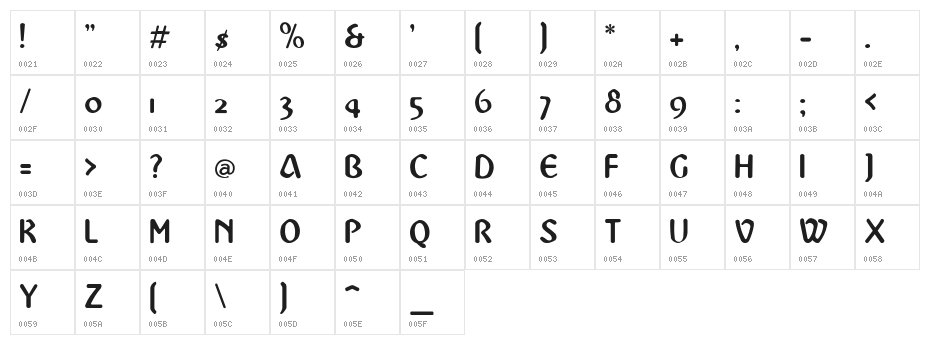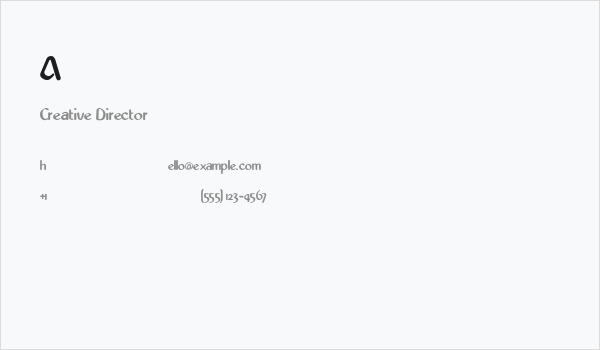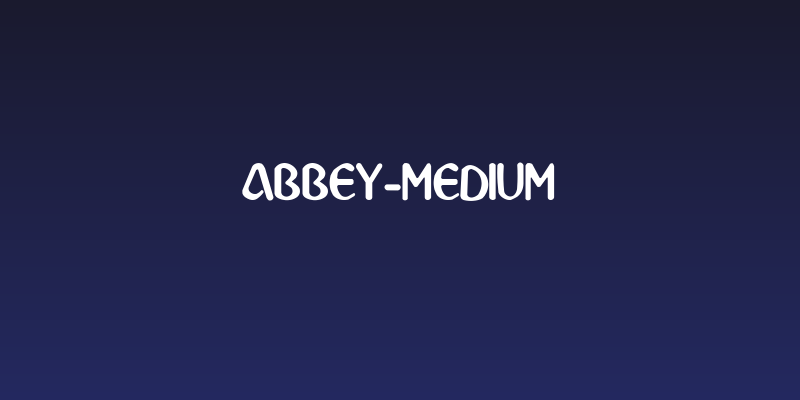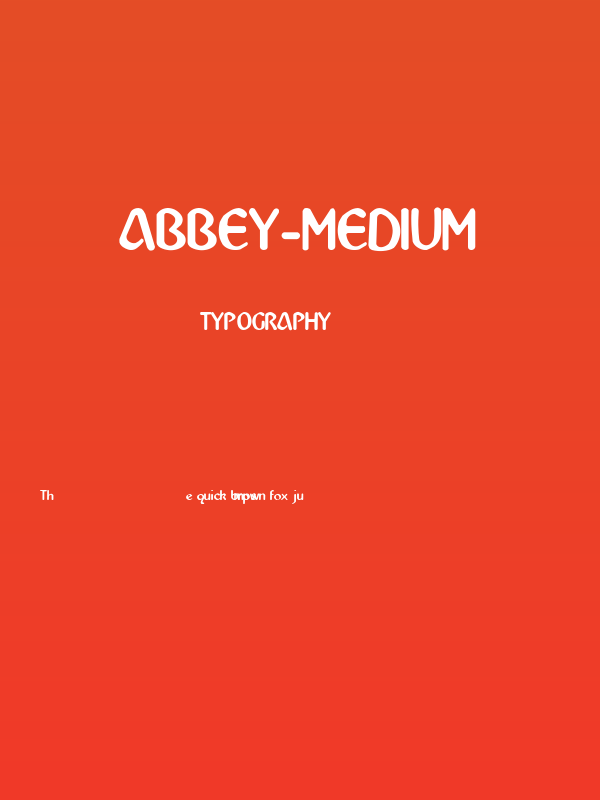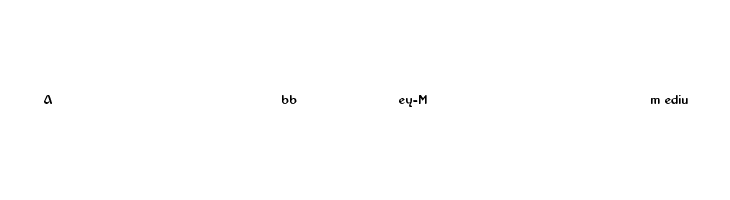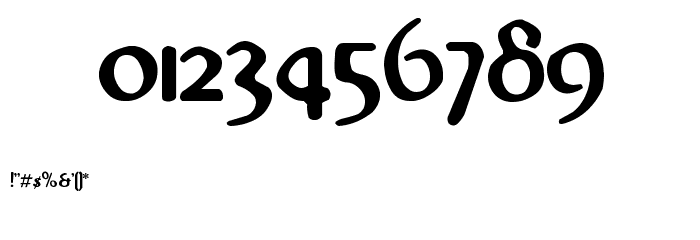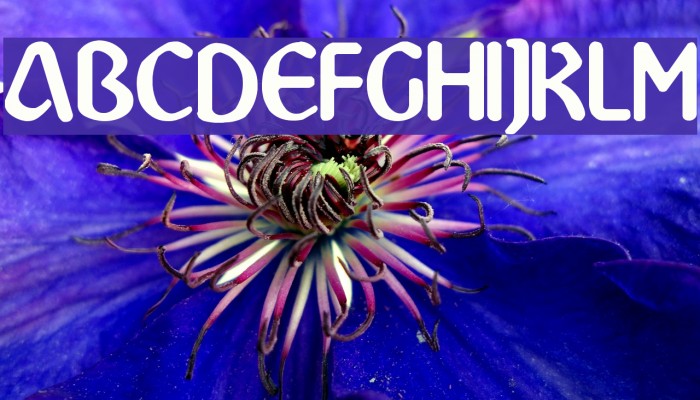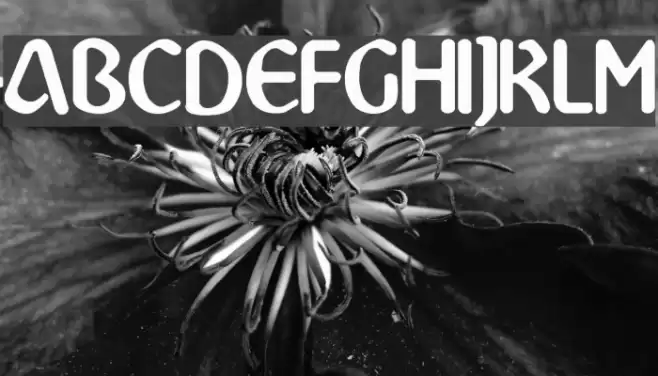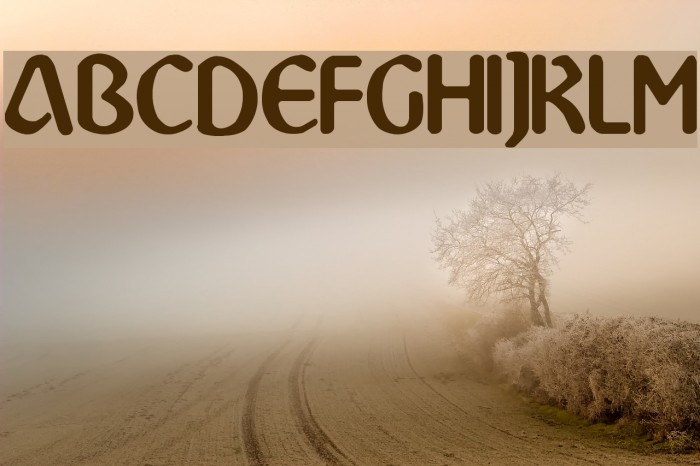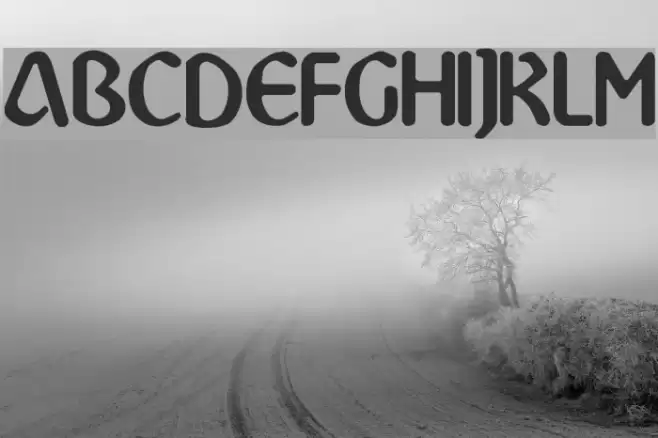
Abbey-Medium Font
| Stile generale | Modern, Decorative |
| Progetti proposti | Ideal for branding, posters, headlines, and packaging designs that require a bold and distinctive look. |